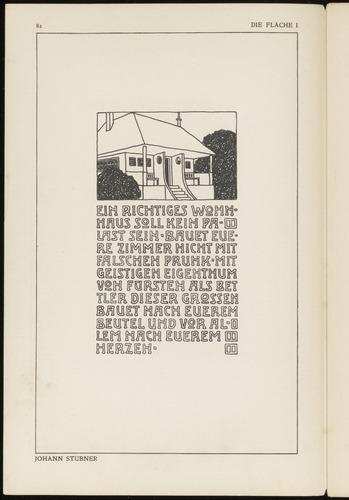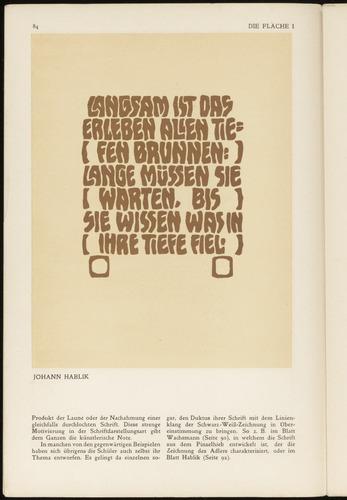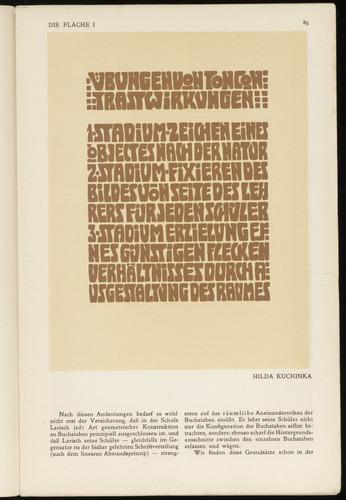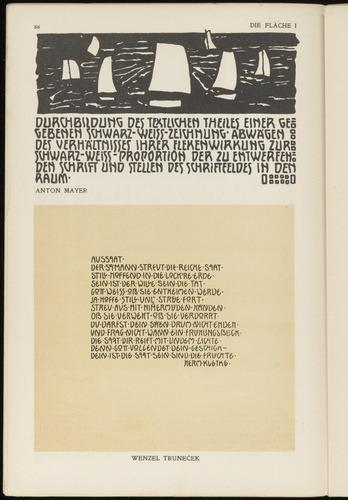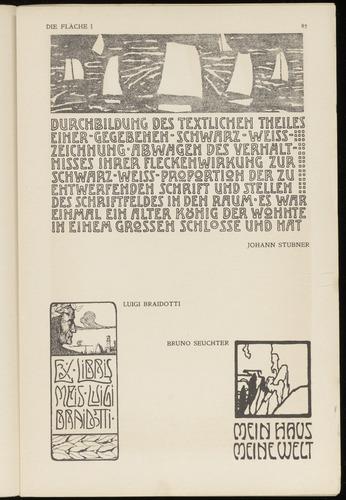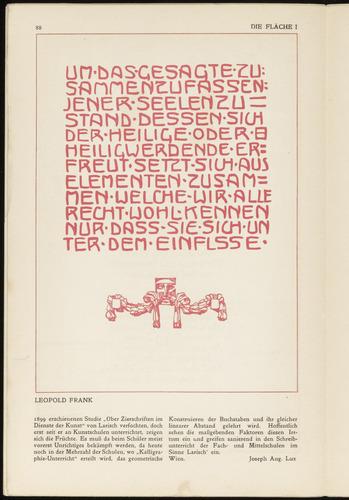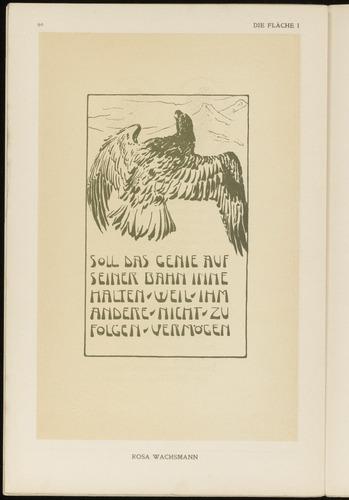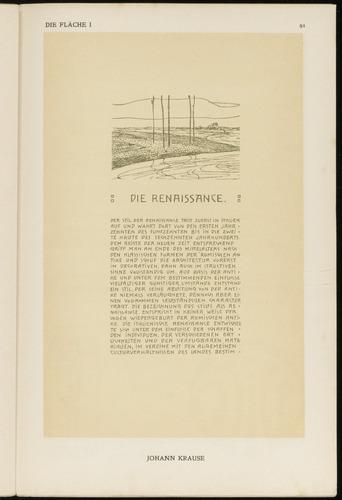
Hier gibts einen Artikel zum Thema »Texte zum Testen von Schriften« und weshalb der »Quick Brown Fox« eher ungeeignet ist.
Das ist eine tolle Sache! Besonders, weil mein selbstgezimmerter proof text mehr als doppelt so lang ist. Vielen Dank!
Das Swash-t (»angewandt«) ist ja allerliebst! :biglove:Das musst du bei einer Digitalisierung unbedingt übernehmen.
Ich hatte eigentlich vor, ein deutsches, ein französisches, und ein amerikanisches Art Nouveau Design Kit zu machen. Anscheinend brauche ich aber auch ein Österreichisches.
Edit: Damit wollte ich nicht Ignoranz der Wiener Sezession ausdrücken, sondern nur, daß ich nicht vorhatte, dafür einen Satz Schriften zu machen.
Natürlich, denn es hieß ja auch überall anders :-D
Jugendstil, Art Nouveau, Modern Style, Secession ...
Ich bin jedenfalls schon mal sehr gespannt, für welche Schriften du dich entscheidest.
Na, alle 🙂
Das größte Problem, aber auch die interessanteste Herausforderung bei diesen Schriften ist m. E. die Verschachtelung. Wenn es sich nur um Großbuchstaben handelt, dann müßte ich 26 Grundformen und ~700 Ligaturen machen. Das läßt sich wohl reduzieren, wenn man gemeinsame Schnittstellen finden kann, die auf mehrere Paare zutreffen. Aber trotzdem - Junge, Junge, das wär doch was! Allerdings habe ich keine Ahnung, wo solche Schriften Verwendung finden könnten. Gut lesbar sind sie ja nicht gerade.
Da die ja damals wohl auch in Blei gekommen sind, denke ich hier weniger an Tonnen von Ligaturen, sondern eher an Contextual Alternates (calt).  Ich liebe calt, da dies auch in Software mit minimaler OpenType-Unterstütung direkt funktioniert. Ich nutze dies z.B. für Schreibschriften, wo ja ebenso das Verschachtelungs-Problem auftritt.
Ich denke, die Beispiele zeigen gemalte Zierschriften ... insofern hatten die Künstler natürlich jede Menge Freiheiten, die es nun technisch zu »beschränken« gilt :-?
In sofern könnte ich mir durchaus eine recht ähnliche "Catfonts  Restricted Font License" für Fonts, die durch ihr Erscheinungsbild geeignet sind, rechsextremes Gedankengut zu verbreiten, und die Gefahr besteht, dass es so interpretiert werden könnte, dass ich mit Bereitstellung dieser Schriftart ebebn auch hinter dieser Ideologie stünde.
Werbung. Klappt sogar
Oh ja, ich überlege gerade, ob sie wohl mein Vermögen verwalten könnten 🤔:hammer:
... Vermögen verwalten..?   Bestimmt nur eine Frage des Honorars!
Das Nudelwerkzeug rotiert nicht, sondern ist in 2 (oder mehr Lagen) in den Kopf der Nudelmaschine eingebaut. Das ganze Teil funktioniert im Prinzip wie ein Fleischwolf. Die Schnecke innen foerdert den Teig und presst ihn durch die Form. Vor der Form, auf der Welle der Schnecke, ist ein Messer angebracht, das mit der Umdrehung der Schnecke rotiert - die Schleifspuren des Messers sind auf dem Bild auch gut zu sehen. Dieses Messer schneidet dann die Nudelscheibchen. Wenn man das Messer weglaesst, kommen Buchstaben-Makkaroni raus. Der Nudelteig, den die Profis verwenden ist uebrigens nochmal um einiges haerter, als der Teig, den Du im Haushalt verwendest. Es waere also kein unloesbares Problem, verschiedene Schrifttypen herzustellen. Man sollte dabei nur beachten, dass der Druck, der notwendig wird, den Teig durch die Form zu pressen, stark ansteigt, wenn man die Wandstaerke des Nudelprofils verringert. Diese Formen gibt's uebrigens auch als Zubehoer zu manchen exotischeren Haushaltsmaschinen - oder Du nimmst Muttis alten Fleischwolf, da waren meist so Formscheiben fuer Spritzgebaeck dabei.
Hey, das könnte man dann aber eben auch als geschicktes Marketing sehen.
Auch ist mir klar, das sich der Anschitt "3e: Diskriminator" kaum rechtswirksam durchsetzen lässt, sondern eher eine Willensäußerung da steht, mit der man eben nur sagt, dass einem die verwendung der Schrift in einem bestimmten Kontext nicht gefällt, und man dieser Nutzung nicht zustimmt. Und wenn es dadurch dann mittels Streisand-Effekt eine deutlich höhere Verebreitung gibt, soll mir das doch recht sein, und sagt dann einer: Warum baust du solche Nazischriften, kann ich diese Menschen auf den Diskriminator in der Lizenz hinweisem,.dass ich eben solche Verwendung nicht aktiv unterstütze, und es diese Schriftarten wahrscheinlich auch ohne die ganz rechten gegeben hätte und darin schlicht ein Modetrend folgte, bei dem auf die verspielten, floralen Formen des Jugendstil eben etas maschimelles, gradliniges folgte, und es letztlich ja auch die Nazis waren, die dem ein Ende setzten.